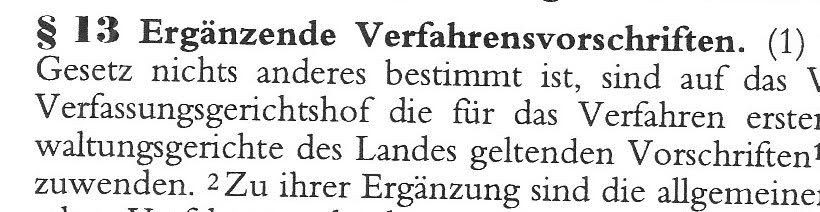
Schriftart gesucht.
Ich suche die folgende Schriftart - ich vermute, es ist die Berthold Garamond oder die Bembo, bin mir aber nicht sicher. Klasse wäre es, wenn ihr mir dazu eine kostenlose Alternative nennen könntet? Wir möchten für für unser Unternehmen ein paar Verhaltensregeln aufstellen und denken, dazu ist diese Schriftart ideal...
Garamond ist schon mal richtig, welche ist bei der Größe schwer zu sagen. Wenn Du es genau wissen musst: hast Du ein größeres Beispiel? Ein R wäre auch hilfreich zur identifizierung.
Eine kostenlose Alternative ist die URW Garamond No. 8 aus dem Ghostscript-Schriftenpacket.
Hier nochmal größer mit "R".
Sieht schwer nach Bembo aus :D
Yupp. Die mit dem Riesen-R™ :D
ja, und auch die Ziffer sind aus einer klassizistischen (Bodoni und Konsorten)
Mir gehts maßgeblich um die dünnere Schrift!
Die fettgedruckten Buchstaben können also außen vor bleiben.
Also ist der Zwischenstand:
- dünn und dick sind unterschiedlich
- dünn ist maßgeblich Bembo
- und die Ziffern und Zeichen sind klassizistisch - also in einer weiteren Schriftart
Aber macht sich denn wirklich jemand die Arbeit und setzt einen Text aus drei oder vier Schriften zusammen. Kann ich mir fast nicht vorstellen - könnte das nicht doch eine eigene Schriftart sein?
Aber macht sich denn wirklich jemand die Arbeit und setzt einen Text aus drei oder vier Schriften zusammen.
Oh, ja. Sie nennen sich Typografen. :-)
könnte das nicht doch eine eigene Schriftart sein?
Nö. Schau Dir mal die Ziffer 3 in Deinem ersten Beispiel («§ 13») an und dann im zweiten Bild die «3» in der Fußnotenziffer. Das sind ganz unterschiedliche Fett-Fein-Kontraste, unterschiedliche Abschlüsse, unterschiedliche Kurven, usw. usf.
Der Text besteht aus zwei verschiedenen Schriftarten. Das Paragrafenzeichen und die Ziffer 13 sind aus der Bodoni Poster, der restliche Text ist aus der Bembo bzw. Bembo Bold gesetzt.
Ich nehme an, dass es für die Bodoni Poster keine kostenlose Alternative gibt, oder?